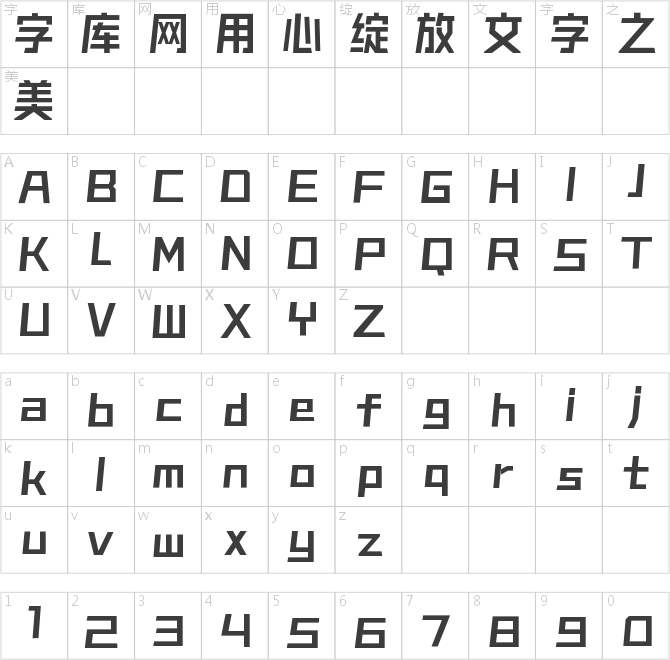
海派腔調(diào)滾石黑
黑體
海派腔調(diào)
海派腔調(diào)滾石黑-粗黑字體字庫(kù)是一款讓人賞心悅目、百看不厭的中文字體,適合各類廣告和產(chǎn)品包裝設(shè)計(jì)應(yīng)用,字體大小1.33MB,格式為ttf字體,上傳用戶是漫步云端,作者/版權(quán)方為銳字潮牌